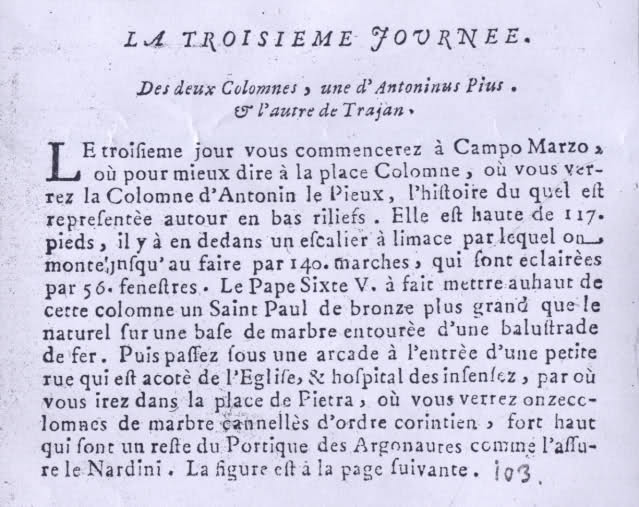
Buchschrift aus 1700
Welche schrift ist das?
ich wil 2 Seiten in diesem Buch ersetzen
in frage kommen ja nur schriften, die alle verwendeten ligaturen und alternativzeichen enthalten. das wären zum beispiel die sabon next, die arno und die garamond premier. der adobe caslon fehlt unter anderem das swash-n, wie es am ende der fünften zeile steht.
ps: gibt es irgendwo einen besseren scan von den seiten?
pps: lass mal das ergebnis sehen, wenn du das komplett nachsetzt.
Schaut gut aus. Jetzt noch ein- bis zweimal skaliert über den Kopierer jagen und man kommt recht nah an das Original.
schau Dir auch mal die sogenannten DayRoman, eine digitalisierte Double Lined Pica von François Guyot aus dem 16ten Jh, an. Die war auch Hausschrift eines englischen Verlag J. Day, daher auch der Name. Die Schrift ist Freeware und gibt es nur in einem Schriftgrad aber mit Expertschnitten und langem-s.
Die könnte auch halbwegs passen. *EDIT* Aber die Italic musst Du Dir dann wo anders her holen. Vielleicht aus einem der anderen Vorschläge?
Ohne jetzt nachzuprüfen, ob die benötigten Glyphen alle vorhanden sind: The Fell Types
guter hinweis – obwohl das swash-n fehlt. hier die de walpergen’s pica:
mit ein bisschen zeit und muße lässt sich bestimmt noch mehr erreichen.